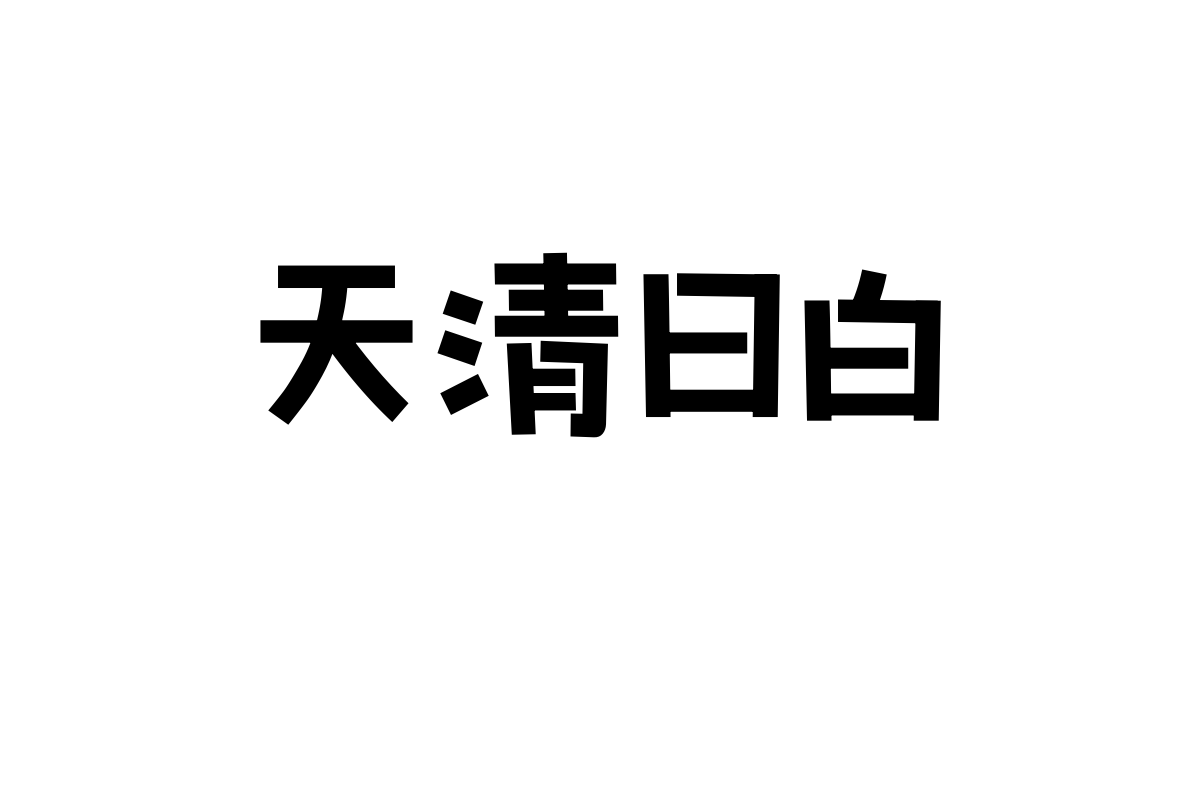
文道手绘体是一款具有独特风格和特色的中文字体。它的设计灵感来源于传统的手写书法,通过现代技术手段进行数字化处理,形成了这款独特的字体。
1. 字形特点:文道手绘体的字形结构紧凑,笔画流畅自然,给人一种简洁而富有韵味的感觉。每个字符的笔画都经过了精心设计,使得整体字形既有规律性又不失个性。
2. 风格特点:文道手绘体的设计风格独特,线条粗细变化丰富,既有粗犷豪放的气势,又有细腻精致的美感。这种风格既适合用于标题、广告等需要强烈视觉冲击力的设计,也适合用于正文、副标题等需要平衡美感的设计。
3. 应用场景:文道手绘体适用于各种场合,如海报、宣传册、杂志、网站、APP界面等。它能够很好地融入不同的设计风格,为设计师提供丰富的创作空间。
总之,文道手绘体是一款独具匠心的中文字体,它融合了传统书法与现代设计的元素,为设计师提供了一个全新的创作平台。无论是在商业还是艺术领域,都能发挥出其独特的魅力。